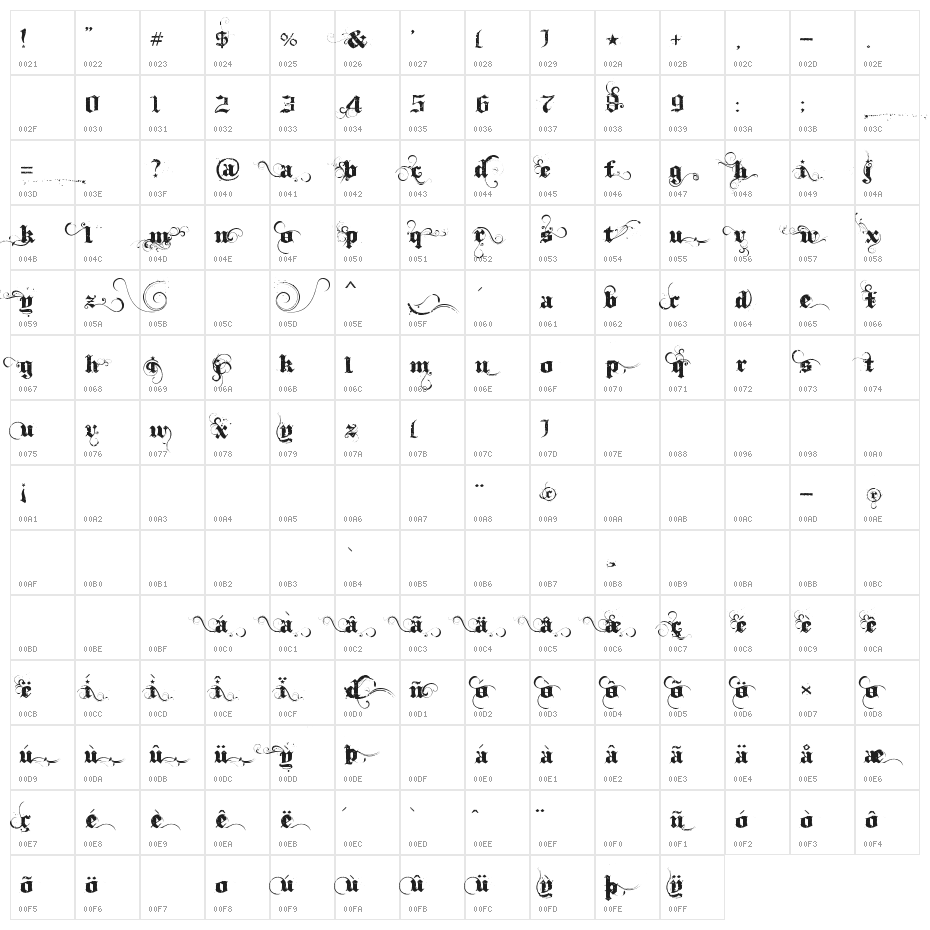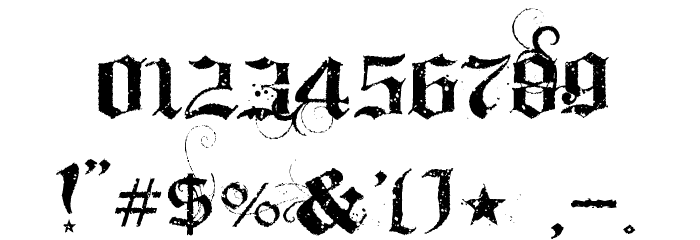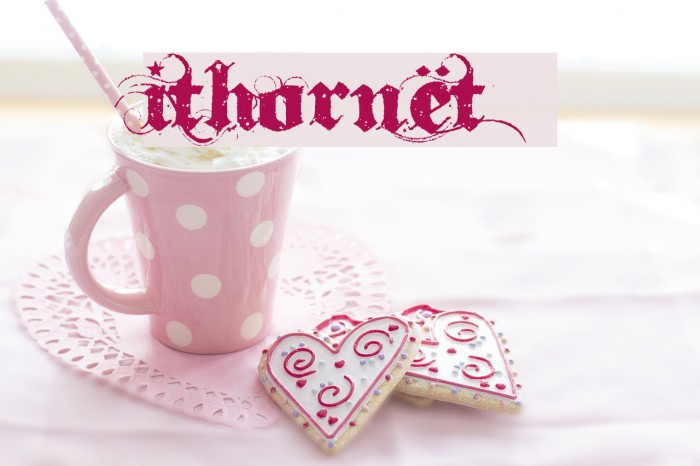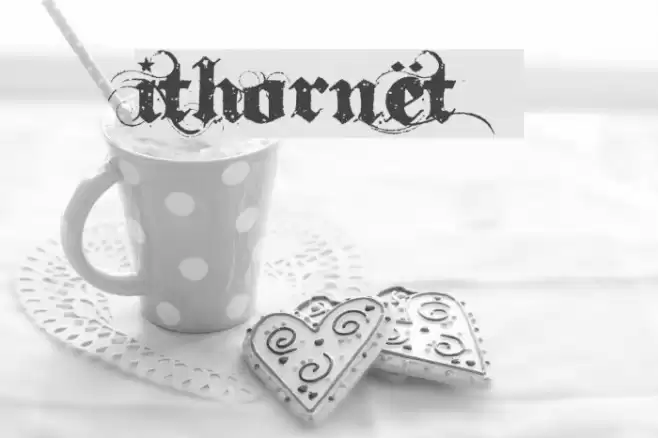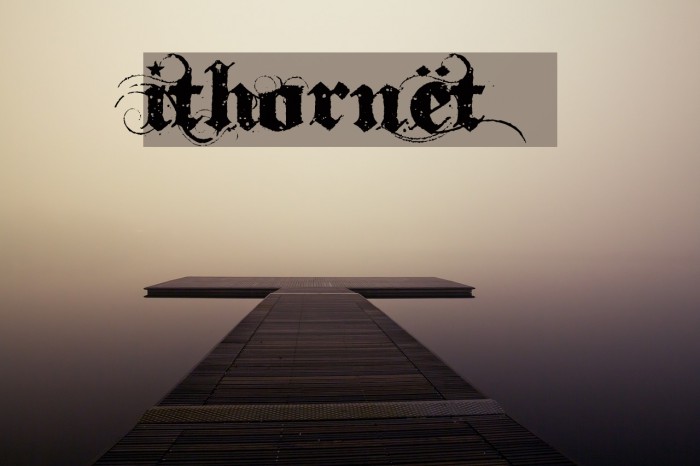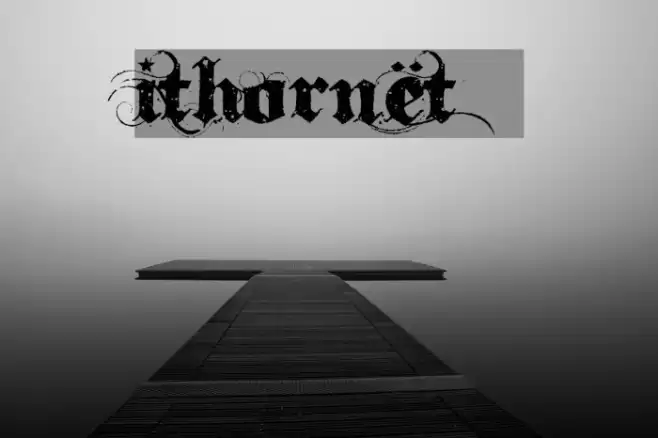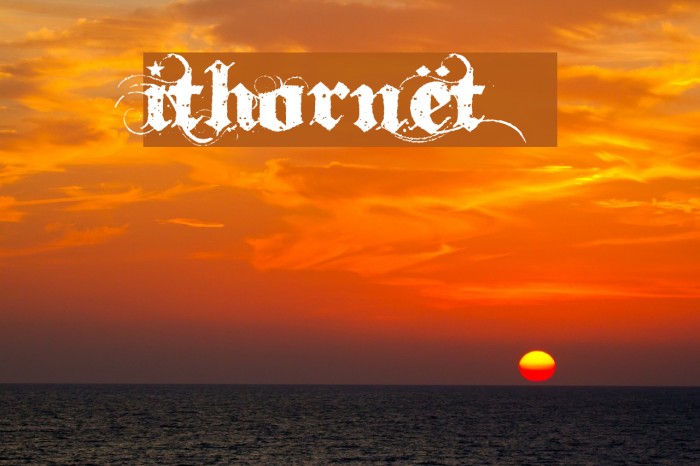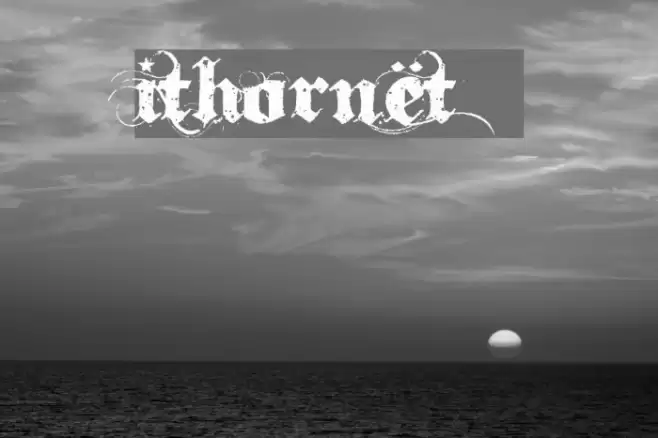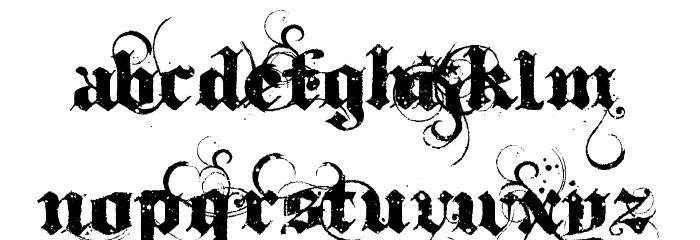
Ithornët Font
✎ Gothic
| Cas d'utilisation | Logos, Headlines, Decorative text |
| Projets proposés | Ideal for wedding invitations, historical-themed posters, book covers, and branding that requires a touch of elegance and drama. |